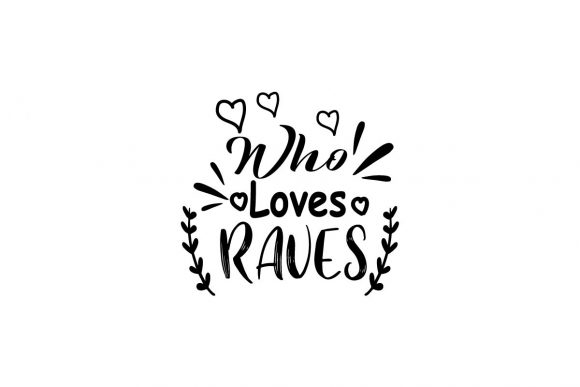
Who Love Raves-Lettering Font
Mencari elemen reka bentuk yang sesuai boleh menjadi mencabar, tetapi Who Love Raves-Lettering Font menawarkan koleksi luar biasa yang menaik taraf karya anda serta-merta.